Thiết kế giao diện là một trong những công đoạn vô cùng quan trọng khi tạo lập web. Trong quá trình này, bên cạnh các yếu tố như bố cục, màu sắc, logo,…lập trình viên còn cần lưu ý đến font chữ. Lựa chọn font chữ chuẩn cho website giúp tạo được ấn tượng tốt cho khách hàng.
Tuy nhiên, hệ thống font chữ hiện có rất đa dạng, không phải lúc nào bạn cũng có thể dễ dàng tìm kiếm được font chữ chuẩn cho website vừa ý. Để việc chọn phông chữ không còn khó khăn, NQ News gợi ý cho bạn những font chữ chuẩn cho website đang được sử dụng phổ biến nhất hiện nay.
Cách chọn font chữ chuẩn cho website
Trước khi tìm hiểu về những font chữ chuẩn hay dùng cho website, bạn cần biết về những lưu ý khi chọn font chữ dưới đây.
- Dễ đọc: Nguyên tắc đầu tiên bạn cần nhớ khi chọn font chữ chuẩn cho website là dễ đọc. Một website dù đẹp đến đâu nhưng font chữ quá to, quá nhỏ hoặc quá rối mắt đều sẽ khiến người đọc phản cảm. Kích thước chuẩn cho font chữ thường là 12 – 14.
- Màu sắc: Màu sắc cũng là yếu tố cần lưu tâm khi chọn font chữ. Màu chữ cần có sự hài hòa với màu nền của website để có thể nổi bật nhưng không gây chói mắt, khiến việc theo dõi thông tin trở nên khó khăn. Tránh sử dụng màu chữ gần hoặc tương phản quá mức với màu nền.
- Phù hợp với mục đích của website: Tùy vào đối tượng phục vụ, mục đích sử dụng mà website có nội dung, concept khác nhau. Những yếu tố này cũng ảnh hưởng đến việc chọn font chữ chuẩn cho website. Một website bán đồ chơi trẻ em nên sử dụng font chữ khác với một trang web làm đẹp. Ngoài ra, hãy chắc rằng font chữ bạn sử dụng không quá cầu kỳ, rườm rà, nó sẽ khiến người đọc mất tập trung.
- Khoảng cách dòng và chữ: Lưu ý đến cách dãn dòng. Khoảng cách phù hợp giữa các dòng trên website khiến người đọc không bị rối mắt, khó chịu khi theo dõi thông tin.
- Chỉ sử dụng 1 loại font chữ: Đừng bao giờ cho rằng trang web có nhiều font chữ sẽ đẹp. Đây là quan niệm sai lầm và nó chỉ khiến trang web của bạn trông rối mắt hơn. Khi chọn font chữ chuẩn cho website chỉ nên dùng 1 hoặc cùng lắm là 2 font chữ cho một trang web. Với các website tiếng Việt, hãy ưu tiên những font Unicode chuẩn để tránh lỗi font lúc hiển thị.
10 font chữ chuẩn cho website khi thiết kế
Nếu bạn đang lấn cấn chưa biết nên chọn font chữ nào khi thiết kế website, hãy tham khảo những gợi ý sau đây. Chúng đều là những font chữ chuẩn cho website đang được sử dụng rộng rãi nhất.
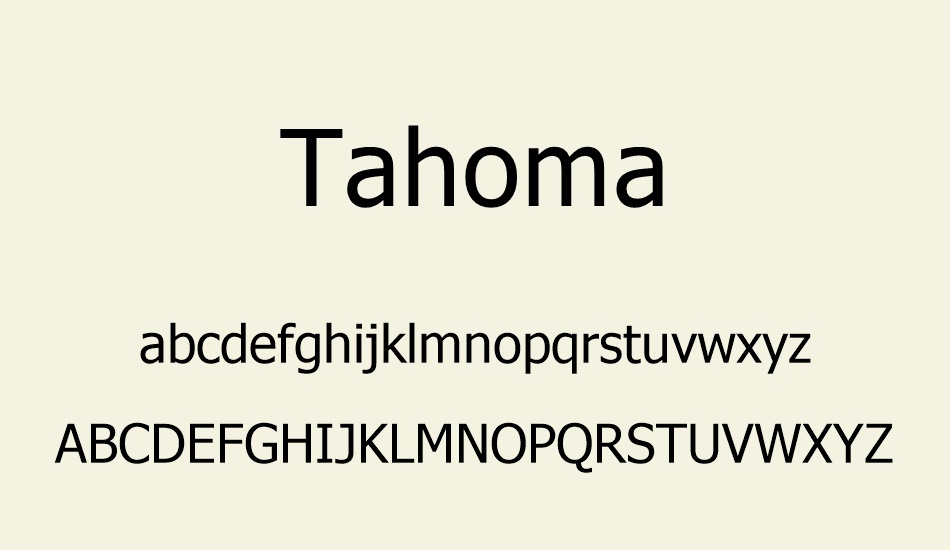
- Arial: Đây là font chữ được dùng phổ biến, rộng khắp trong quá trình thiết kế website. Nó được ưu ái bởi đơn giản, dễ nhìn. Trên Windows, nó còn được sử dụng để thay thế những font chữ khác.
- Bookman: Đây là lựa chọn xuất sắc nếu bạn đang tìm kiếm một font chữ chuyên dụng cho tiêu đề. Nó mang lại khả năng đọc dễ dàng ngay khi ở kích thước nhỏ. Đây cũng là nguyên nhân khiến Bookman lọt vào top các font chữ chuẩn cho website được dùng nhiều nhất.
- Tahoma: Nằm trong top các font chữ chuẩn cho website thông dụng, đẹp, rõ ràng, nhẹ nhàng nhưng dễ thu hút Tahoma trở thành cái tên được khá nhiều lập trình viên sử dụng trong thiết kế web. Font chữ này tương đối đa năng, bạn có thể sử dụng nó để làm tiêu đề, content, menu,…
- Comic Sans: Phông chữ mang phong cách nhí nhảnh, đáng yêu và có chút…thiếu nghiêm túc này là lựa chọn tuyệt vời nếu bạn đang xây dựng một trang web bán đồ trẻ em hoặc mang tính giải trí. Nó tạo hiệu quả thị giác tốt hơn nhiều so với các phông chữ như Times New Roman hay Arial.
- Helvetica: Nằm trong dòng sans serif, Helvetica có chiều cao, hỗ trợ đọc trong trường hợp các ký tự có khoảng cách quá gần nhau hoặc kích thước nhỏ. Đây là Font chữ chuẩn cho website với nhiều phiên bản phục vụ cho tiếng Latin, Hebrew, Urdu, Cyrillic, Hy, Nhật, Hindi, Khmer, Hàn và Việt Nam.
- Courier New: Là font chữ tương đối phổ biến, quen thuộc với những ai hay làm việc cùng trình soạn thảo. Đây là lựa chọn không thể phù hợp hơn nếu bạn có nhu cầu trình bày những yếu tố riêng biệt trong một văn bản.
- Garamond: Đây cũng là font chữ chuẩn cho website được sử dụng khá phổ biến trên thế giới. Font chữ này được phát triển, tích hợp tại phần lớn thiết bị của Windows. Tuy vậy, nó có nhược điểm là hỗ trợ cho tiếng Việt không quá ổn, vần 2 dấu thường bị lỗi hiển thị.
- Times New Roman: Đây là font chữ mà bất cứ ai từng soạn thảo văn bản đều đã dùng đến. Nó tương đối rõ ràng, rành mạch, phù hợp với các trang báo chí hay tài liệu. Hiện nó được tích hợp sẵn trên Windows và là lựa chọn đáng cân nhắc nếu bạn chưa đưa ra quyết định về font chữ chuẩn cho website.
- Calibri: Sang trọng, nhỏ gọn là yếu tố khiến Calibri trở thành lựa chọn hấp dẫn khi thiết kế giao diện website. Nên sử dụng cỡ chữ từ 12 trở lên để nội dung trang web của bạn hiển thị rõ ràng và không kém phần bắt mắt.
- Georgia: Sở hữu độ lớn, kích thước riêng của mình, Georgia cũng là lựa chọn đáng cân nhắc khi lựa chọn font chữ chuẩn cho website. Tuy nhiên, nếu sử dụng font chữ này, hãy đảm bảo rằng bạn không dùng thêm một font khác bởi Georgia luôn có vẻ nhỉnh hơn các font chữ khác.